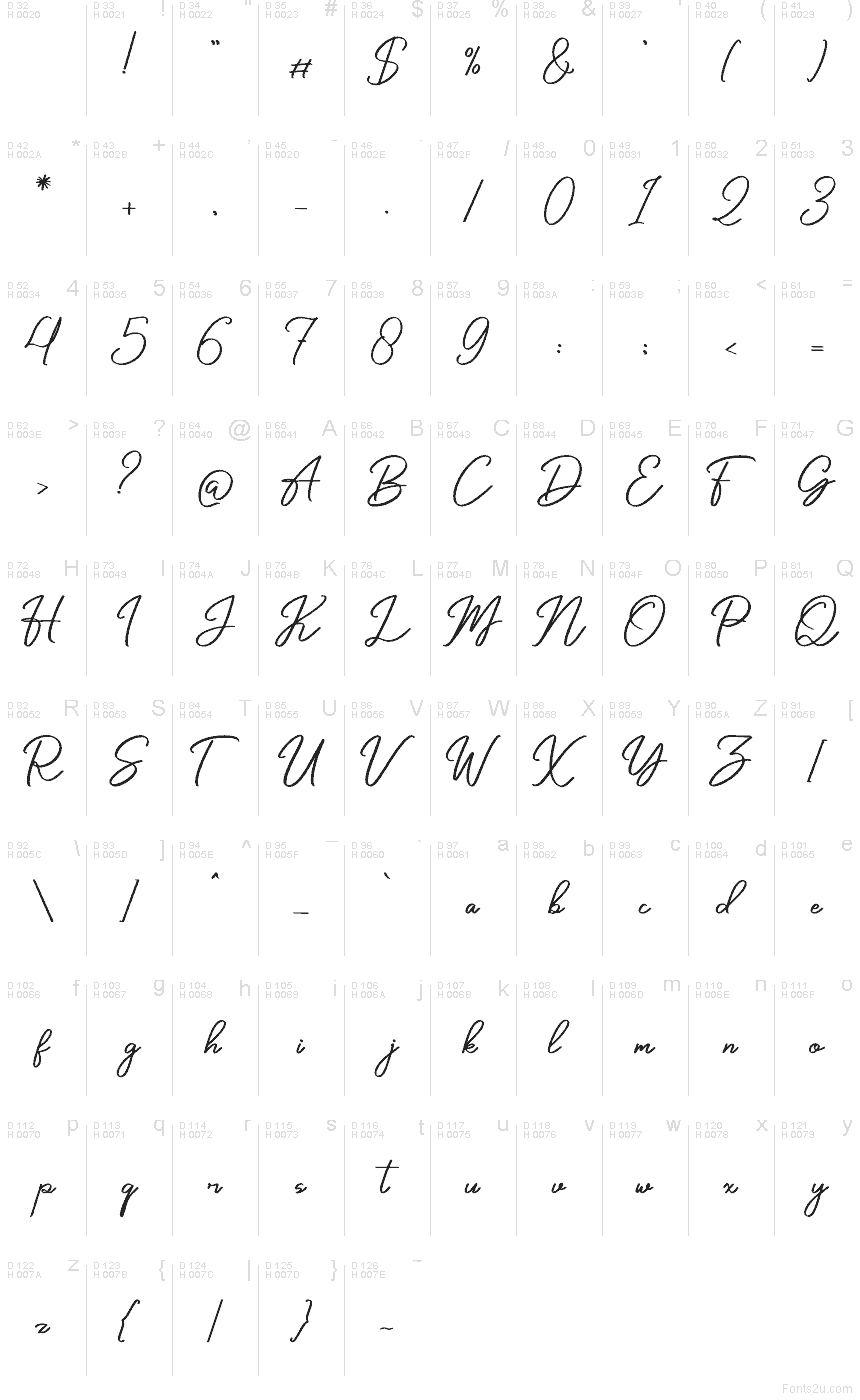
Yuanitta
Yuanitta par Denustudios est une police manuscrite gratuite, façonnée par de longues boucles et un mouvement fluide, presque comme une signature. Ses courbes hautes et ses liaisons basses et fluides donnent aux lettres un rythme balayé, évoquant davantage le mouvement rapide d'un stylo qu'une calligraphie trop travaillée.
Ce dynamisme est parfait pour les logos de boutiques, le packaging, les citations sur les réseaux sociaux, les titres d'invitations et le branding beauté où une touche personnelle est recherchée. Les titres courts et les designs basés sur des noms en profitent particulièrement, car les traits d'entrée étendus et le flux décontracté confèrent à chaque mot une élégance naturelle sans être trop ornée.